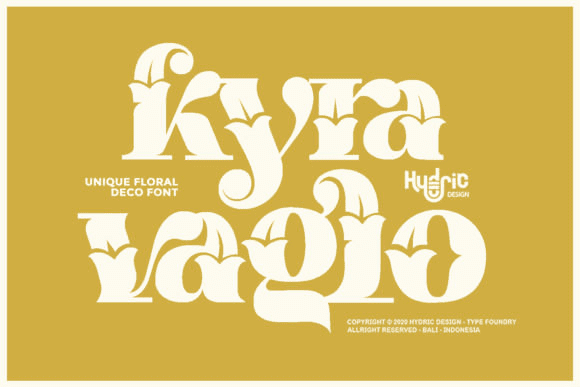
Название: Kyra Vaglo Font
Кира Вагло - очаровательный декоративный шрифт.
Влюбитесь в его аутентичность и используйте его для создания великолепных приглашений, красивого стационарного искусства, привлекательных сообщений в социальных сетях и милых поздравительных открыток.
Название: Kyra Vaglo Font
Кира Вагло - очаровательный декоративный шрифт.
Влюбитесь в его аутентичность и используйте его для создания великолепных приглашений, красивого стационарного искусства, привлекательных сообщений в социальных сетях и милых поздравительных открыток.